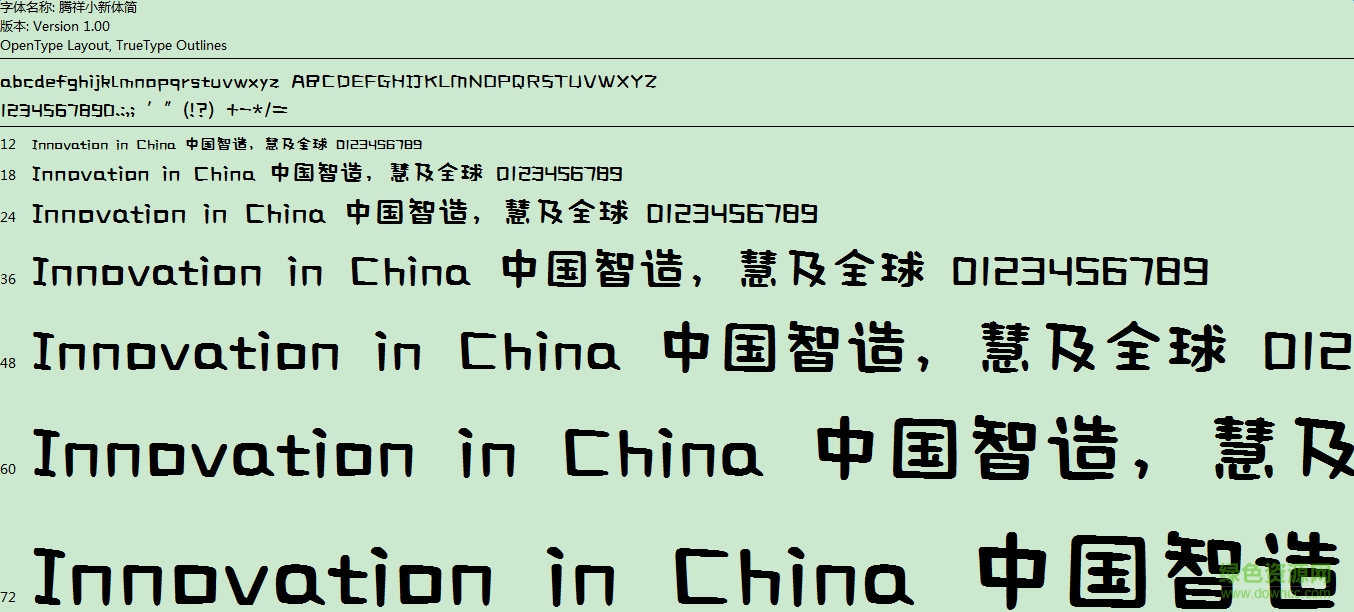
騰祥小新體簡(jiǎn)
騰祥小新體簡(jiǎn)是一款騰祥出品的簡(jiǎn)體字體,美工設(shè)計(jì)、海報(bào)廣告設(shè)計(jì)、藝術(shù)設(shè)計(jì)等方面都可以使用,小編為大家?guī)?lái)免費(fèi)下載地址,大家快來(lái)綠色資源網(wǎng)踴躍下載哦!
騰祥小新體簡(jiǎn),一款非常工整舒暢的字體,文字排版也可以使用喲,溫潤(rùn)自得。